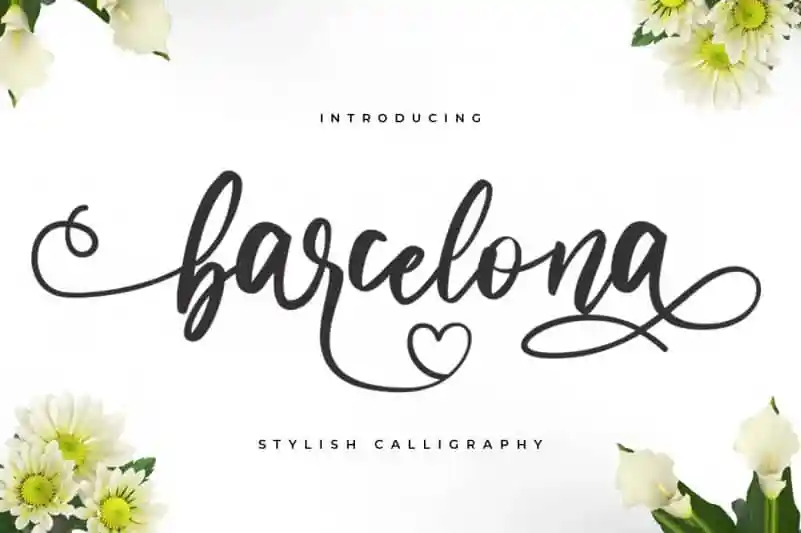
Barcelona Calligraphy Font – Download Grátis
A Barcelona Calligraphy Font é uma deliciosa tipografia de calligrafia moderna que se destaca pela sua linha suave e linhas variáveis na base. O resultado é um conjunto de caracteres incrivelmente bonitos e elegantes, com formas perfeitas e alternativas impressionantes. Para qualquer idéia criativa, essa fonte transformará seu trabalho em verdadeiros trabalhos de arte! Ideal para designers que buscam uma combinação atraente entre a modernidade e o encanto da calligrafia tradicional. Não hesite em experimentar Barcelona Calligraphy Font para agregar um toque sofisticado a seus projetos gráficos.